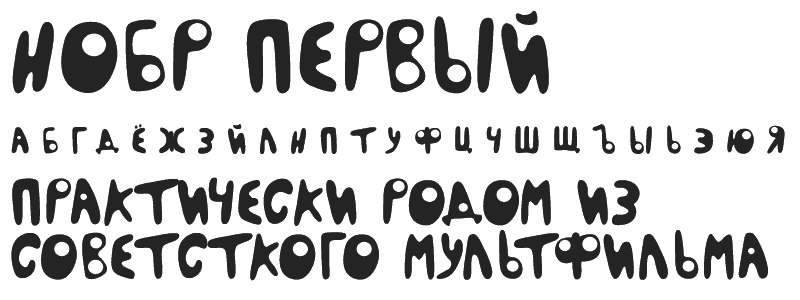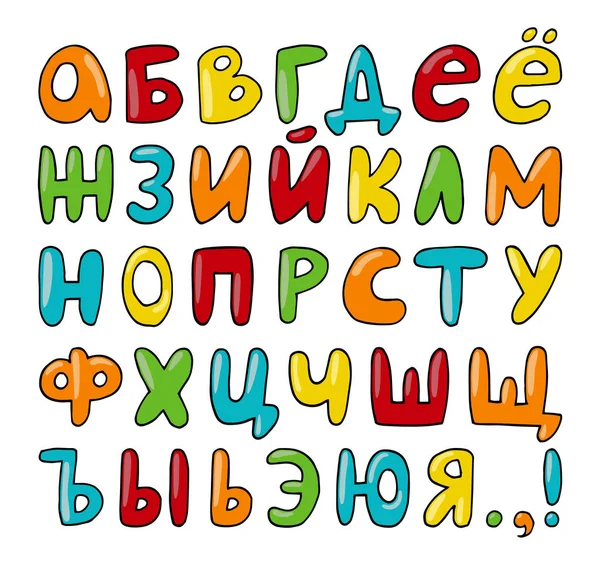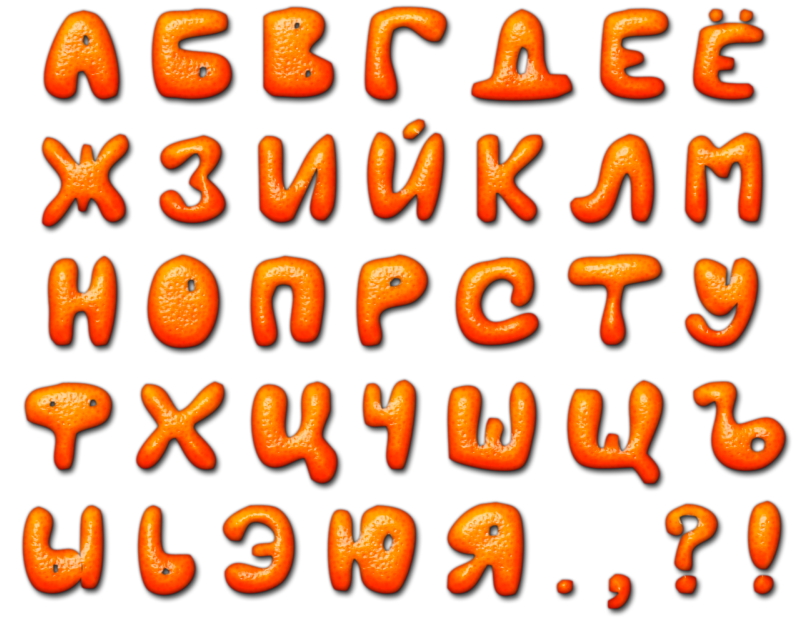
Смешной русский шрифт: Веселые мультяшные шрифты в количестве 15 штук
Веселые мультяшные шрифты в количестве 15 штук
Здравствуйте, дорогие друзья. Давненько я не выкладывал шрифты, которые пользовались большой популярностью у меня сайте. И тут столкнулся с поиском мультяшного шрифта для одного лого и решил сделать сборку из 15-и веселых мультяшных кириллических шрифтов. Некоторые шрифты из этой сборки встречаются в предыдущих моих постах, но я все равно выложил, чтобы было из чего выбрать. Тут есть шрифт из Disney, Ледникового периода, Незнайки на Луне. Каждый шрифт вы сможете скачать отдельно прямо с моего сервера без помощи каких-либо файлообменников и, самое главное, совершенно бесплатно.
Рисованный мультяшный кириллический шрифт
Классный веселый русский шрифт
Кириллический шрифт Disney
Жирный кириллический шрифт из мультика
Стильный рисованный мультяшный шрифт
Веселый жирный шрифт для титров мультика
Контурный мультяшный русский шрифт
Классный веселый кириллический шрифт
Контурный моноширинный мультяшный шрифт
Моноширинный мультяшный кириллический шрифт
Шрифт для титров в мультике
«Безалаберный» мультяшный кириллический шрифт
Русский шрифт из «Незнайка на луне»
Строгий, но веселый шрифт в кириллической раскладке
Тонкий мультяшный шрифт
Вот все 15 кириллических шрифтов из этой сборки, которые можно использовать для титров мультика или веселого фильма, для создания веселого яркого логотипа, баннера на детскую тематику.
Lato — современный и читабельный шрифт, что делает его идеальным практически для любого вида презентаций. Однако он прекрасно подходит для передачи вашего профессионализма и в pitch deck, как мы показали в этих примерах.
Шрифт для презентации №2: Roboto
Еще один отличный шрифт для презентаций — это Roboto. Это еще один базовый шрифт с засечками, который подходит для различных отраслей и видов презентаций.
Roboto — идеальный шрифт для основного текста, как мы видим в презентации ниже.
В Roboto все основные абзацы легко читаются, они выглядят профессионально и хорошо оформлены.
Ниже мы видим, как Roboto используется в презентации, посвященной приложениям для тренировок.
Здесь он также выбран в качестве базового шрифта для основного текста презентации. Это говорит о том, что данный шрифт можно использовать практически для любого формата презентаций, а также в различных отраслях.